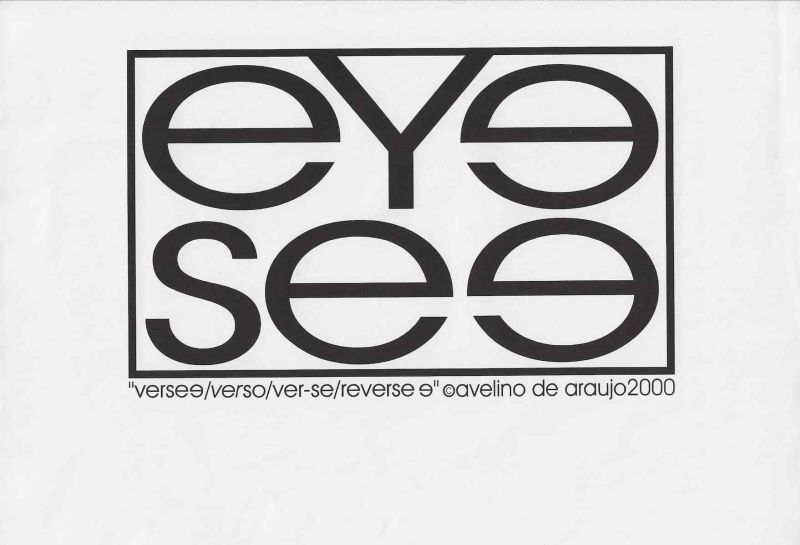
Verse e verso ver se reverse e é uma impressão gráfica de Avelino de Araújo realizada em 2000, vinculada à poesia visual, à poesia experimental, à arte conceitual, à tipografia e às investigações intersígnicas desenvolvidas no campo do Poema Processo.
Verse e verso ver se reverse e é uma impressão gráfica de Avelino de Araújo realizada em 2000, vinculada à poesia visual, à poesia experimental, à arte conceitual, à tipografia e às investigações intersígnicas desenvolvidas no campo do Poema Processo. A composição apresenta grandes caracteres tipográficos pretos organizados dentro de uma moldura retangular. Na parte superior, duas letras e espelhadas aparecem nas extremidades e são conectadas por uma forma central semelhante à letra Y, formando visualmente a palavra inglesa eye, que significa olho. Na parte inferior, a combinação das letras s, e e e produz uma configuração próxima da palavra inglesa see, que significa ver. A aproximação entre eye e see relaciona o órgão da visão ao ato de enxergar, estabelecendo um jogo entre imagem, palavra, percepção e leitura. O título apresenta a sequência verse e, verso, ver se, reverse e e explora transformações fonéticas, visuais e semânticas produzidas pela fragmentação e reorganização das palavras. Verse pode ser lido como forma verbal relacionada ao ato de ver e também como referência à palavra inglesa verse, correspondente a verso poético. Verso pode indicar linha de poema, lado posterior de uma folha ou sentido oposto ao anverso. Ver se introduz a ideia de observar, confirmar, experimentar ou reconhecer. Reverse e propõe a inversão da letra e, procedimento visível nas formas espelhadas presentes na composição. O título funciona como instrução de leitura, jogo verbal e demonstração do processo visual empregado pelo artista. As letras podem ser observadas da esquerda para a direita, da direita para a esquerda, por semelhança sonora, por espelhamento e por associação entre português e inglês. A obra transforma a tipografia em estrutura poética e faz com que leitura e visão ocorram simultaneamente. As letras e apresentam orientação invertida em diferentes posições, enquanto os elementos centrais criam eixos de simetria e estabelecem uma relação entre frente, verso, reflexo e reversão. A composição também pode ser compreendida como investigação sobre o olhar, a identidade, o espelho, a percepção e os limites entre linguagem verbal e imagem. O contraste entre preto e fundo claro reforça a legibilidade dos caracteres e produz grande impacto visual. A moldura organiza a composição como campo fechado, cartaz, emblema ou diagrama linguístico. Na região inferior aparecem o título completo, o símbolo de autoria, o nome Avelino de Araújo e o ano 2000. A obra integra a produção do artista baseada na apropriação de letras, palavras, ambiguidades linguísticas, espelhamentos e códigos gráficos como instrumentos de experimentação poética. Palavras chave para indexação: Avelino de Araújo, Verse e verso ver se reverse e, 2000, impressão gráfica, poesia visual brasileira, poema visual, poesia experimental, arte conceitual, Poema Processo, eye, see, olho, visão, ato de ver, verso, reverso, espelhamento, inversão tipográfica, tipografia experimental, jogo de palavras, linguagem bilíngue, português e inglês, texto imagem, semiótica, intersigno, percepção visual, comunicação visual, arte gráfica brasileira, múltiplo gráfico, arquivo de poesia visual, arte brasileira do século vinte, produção artística do ano 2000.TEXT FOR THE SALSA PROGRAM IN ENGLISH: Verse e verso ver se reverse e is a graphic print by Avelino de Araújo produced in 2000 and associated with visual poetry, experimental poetry, conceptual art, typography and intersemiotic investigations developed within the field of the Poema Processo movement. The composition presents large black typographic characters arranged inside a rectangular frame. In the upper section, two mirrored forms of the letter e appear at the sides and are connected by a central structure resembling the letter Y, visually creating the English word eye. In the lower section, the combination of the letters s, e and e creates a configuration close to the English word see. The relationship between eye and see connects the organ of vision with the act of looking, establishing a play among image, word, perception and reading. The title presents the sequence verse e, verso, ver se, reverse e and explores phonetic, visual and semantic transformations produced through fragmentation and rearrangement. Verse may be understood as a verbal construction related to seeing and also as the English word for a line of poetry. The Portuguese word verso may indicate a poetic line, the reverse side of a sheet or a position opposed to the front. Ver se introduces the idea of looking, checking, experimenting or recognizing. Reverse e proposes the inversion of the letter e, a procedure clearly visible in the mirrored forms of the composition. The title functions as a reading instruction, verbal game and demonstration of the visual process employed by the artist. The letters may be observed from left to right, from right to left, through phonetic similarity, through mirroring and through associations between Portuguese and English. The work transforms typography into poetic structure and makes reading and seeing occur simultaneously. The forms of the letter e appear in reversed orientations, while the central elements create axes of symmetry and establish relationships among front, back, reflection and reversal. The composition may also be understood as an investigation into vision, identity, mirrors, perception and the boundaries between verbal language and image. The contrast between black and the light background reinforces the legibility of the characters and creates strong visual impact. The frame organizes the composition as a closed field, poster, emblem or linguistic diagram. The lower area contains the full title, the authorship symbol, the name Avelino de Araújo and the year 2000. The work belongs to the artist production based on the appropriation of letters, words, linguistic ambiguities, mirrored forms and graphic codes as instruments of poetic experimentation. Keywords for indexing: Avelino de Araújo, Verse e verso ver se reverse e, 2000, graphic print, Brazilian visual poetry, visual poem, experimental poetry, conceptual art, Poema Processo, eye, see, vision, act of seeing, verse, reverse, mirroring, typographic inversion, experimental typography, wordplay, bilingual language, Portuguese and English, text image, semiotics, intersign, visual perception, visual communication, Brazilian graphic art, graphic multiple, visual poetry archive, twentieth century Brazilian art, artistic production of the year 2000.
Impressão gráfica em tinta preta sobre papel claro, formada por caracteres tipográficos de grandes dimensões inseridos em uma moldura retangular. A composição está organizada em duas faixas principais. Na faixa superior aparecem duas letras e em orientações opostas, posicionadas ao redor de uma estrutura central semelhante à letra Y, possibilitando a leitura visual de eye. Na faixa inferior aparecem uma grande letra s e duas letras e em diferentes orientações, formando uma configuração associada à palavra see. Os caracteres ocupam quase toda a área interna da moldura e apresentam linhas espessas, curvas amplas e elevado contraste. A simetria aproximada, o espelhamento e a inversão dos caracteres criam uma leitura bidirecional. Abaixo da moldura encontra se a inscrição verse e, verso, ver se, reverse e, seguida pelo símbolo de autoria, pelo nome Avelino de Araújo e pelo ano 2000. A peça pode ser classificada como poema visual, impressão de artista, múltiplo gráfico, estudo tipográfico e documento conceitual, sendo relevante para pesquisas sobre Avelino de Araújo, Poema Processo, poesia visual, semiótica, percepção, bilinguismo, espelhamento, leitura, visão e produção gráfica brasileira.OBSERVATION TEXT IN ENGLISH: Graphic print in black ink on light colored paper formed by large typographic characters placed inside a rectangular frame. The composition is organized into two principal sections. The upper section contains two forms of the letter e in opposite orientations positioned around a central structure resembling the letter Y, enabling the visual reading of eye. The lower section contains a large letter s and two forms of the letter e in different orientations, creating a configuration associated with the word see. The characters occupy almost the entire internal area of the frame and present thick lines, broad curves and strong contrast. Approximate symmetry, mirroring and character inversion create a bidirectional reading. Below the frame appears the inscription verse e, verso, ver se, reverse e, followed by the authorship symbol, the name Avelino de Araújo and the year 2000. The piece may be classified as a visual poem, artist print, graphic multiple, typographic study and conceptual document, making it relevant to research on Avelino de Araújo, Poema Processo, visual poetry, semiotics, perception, bilingualism, mirroring, reading, vision and Brazilian graphic production.
Verse e verso ver se reverse e is a graphic print by Avelino de Araújo produced in 2000 and associated with visual poetry, experimental poetry, conceptual art, typography and intersemiotic investigations developed within the field of the Poema Processo movement.